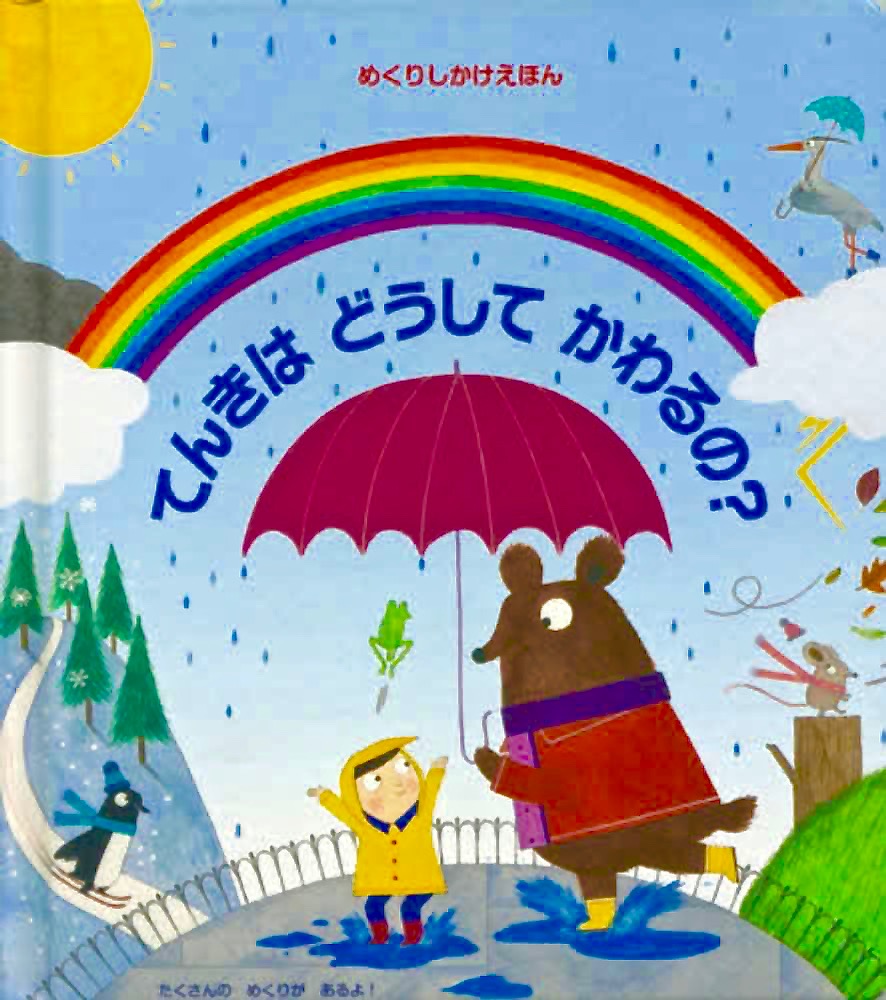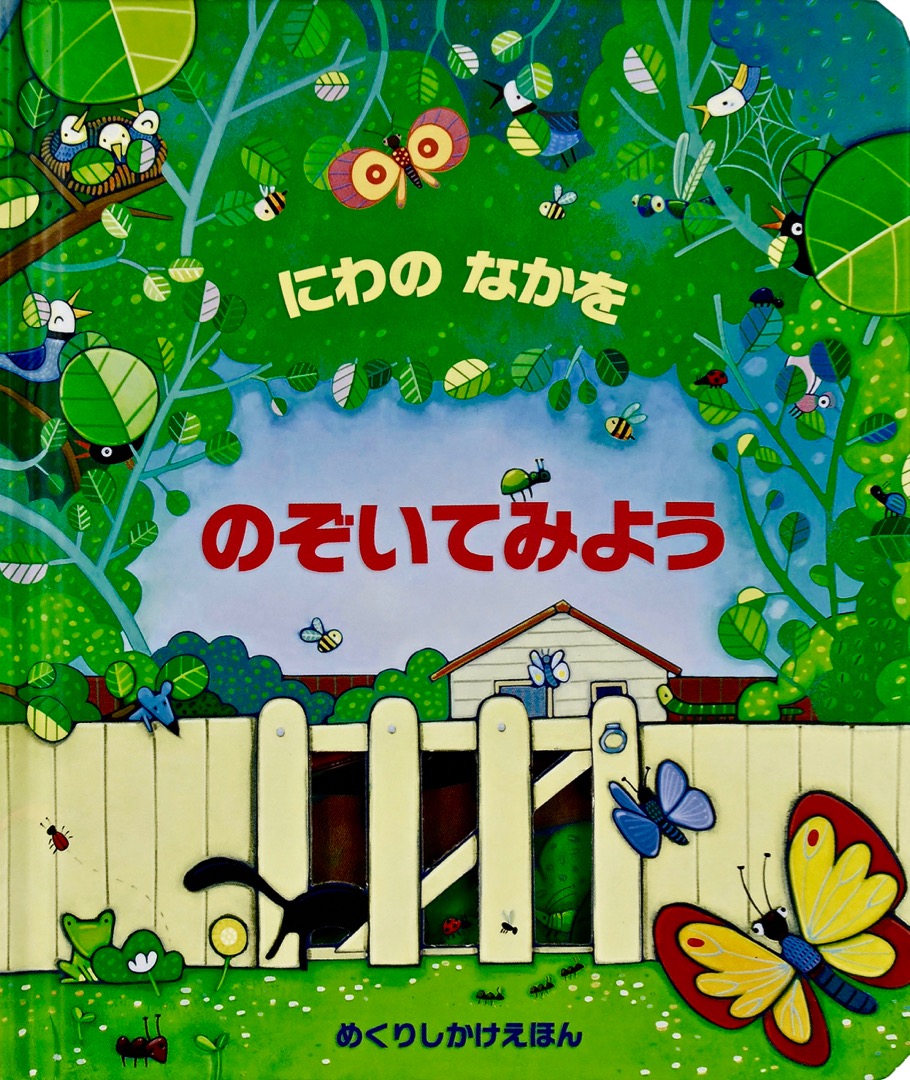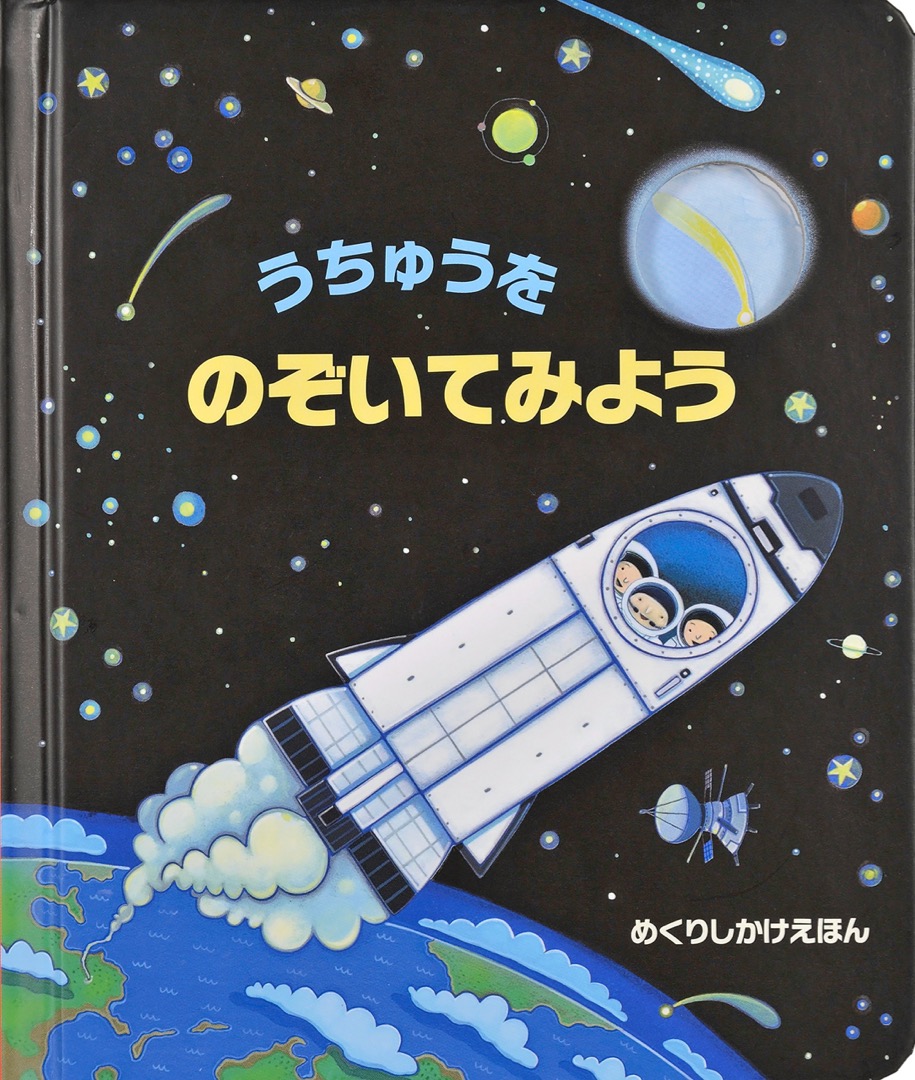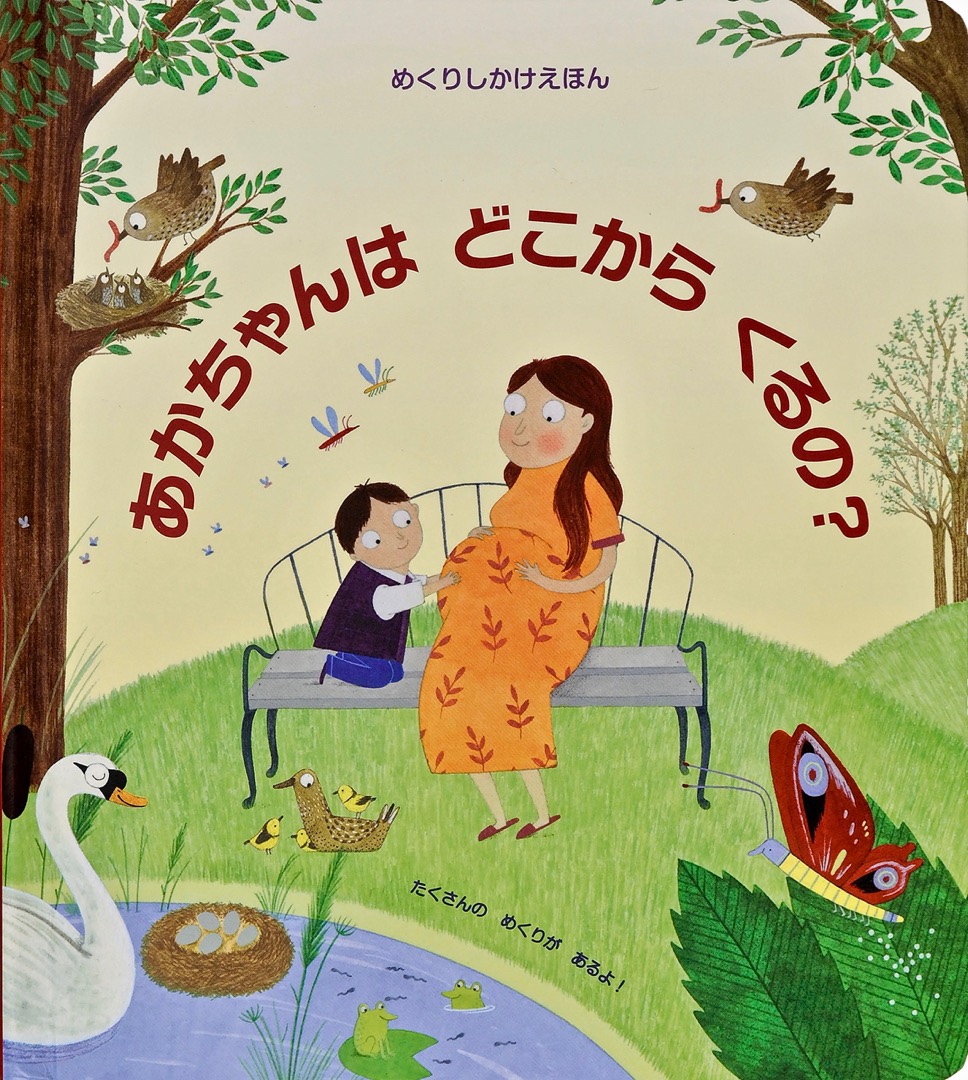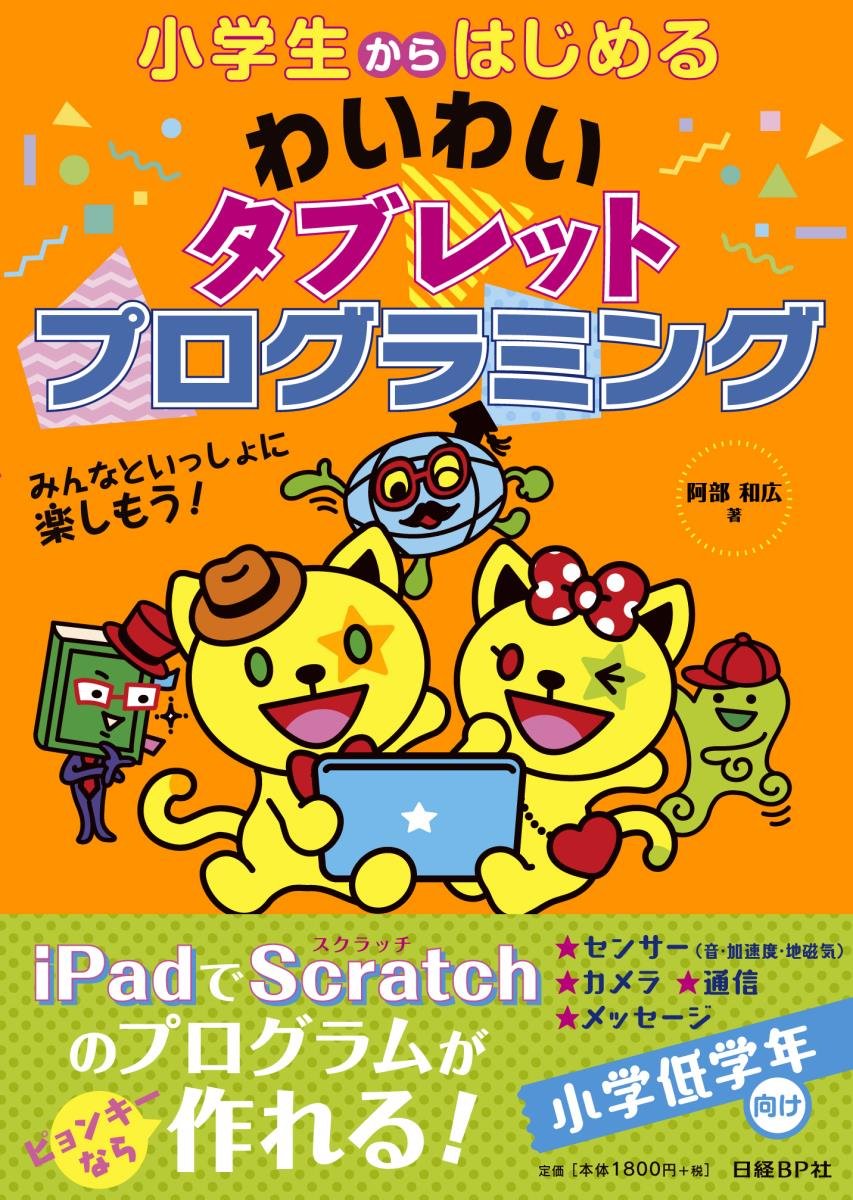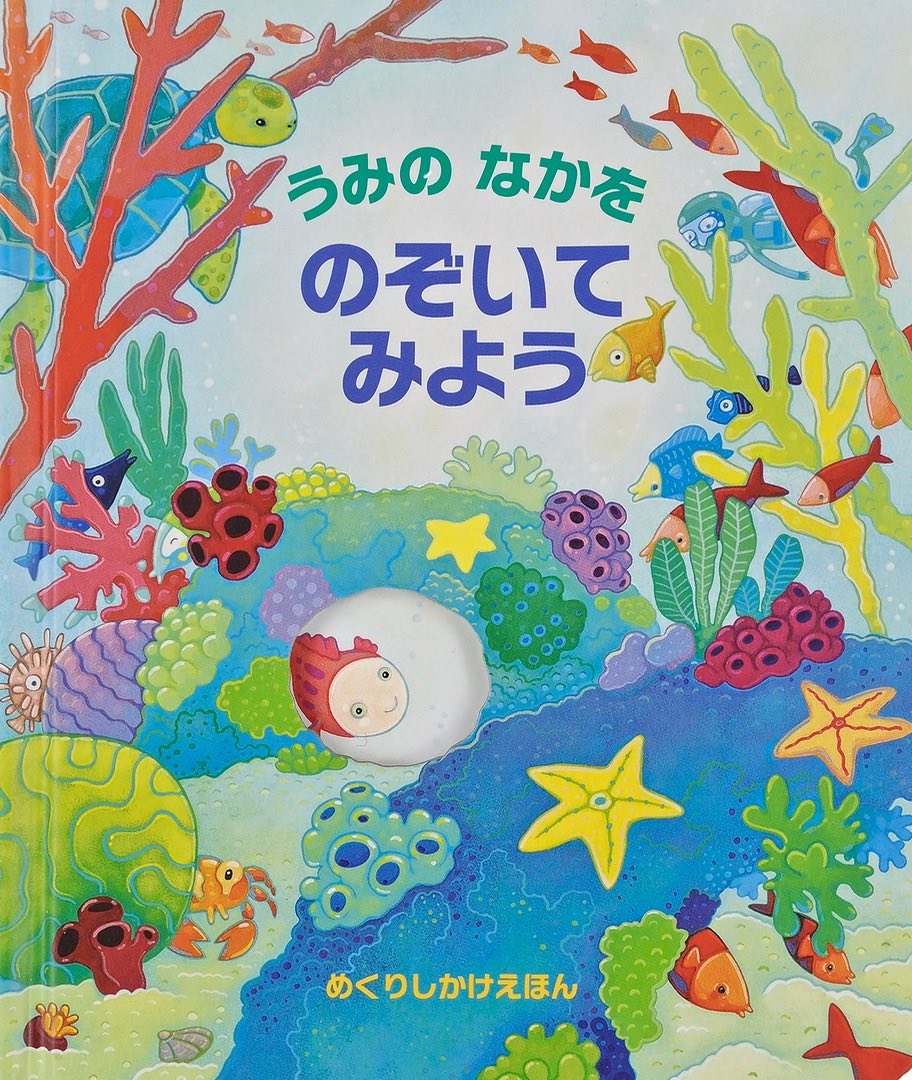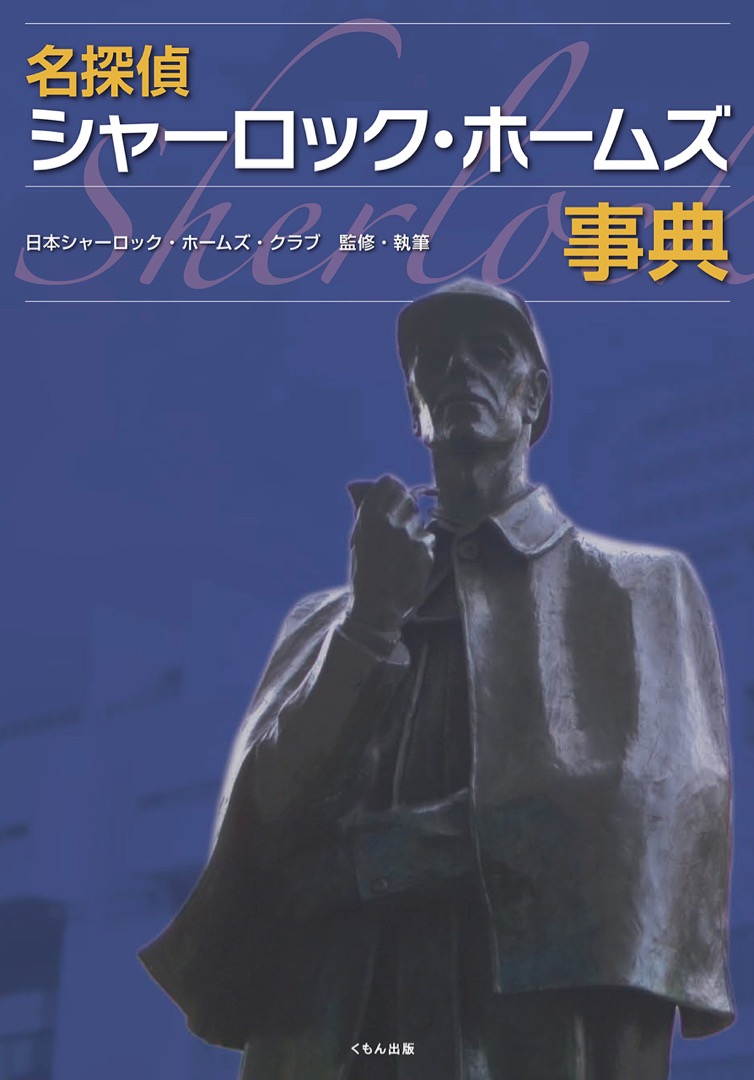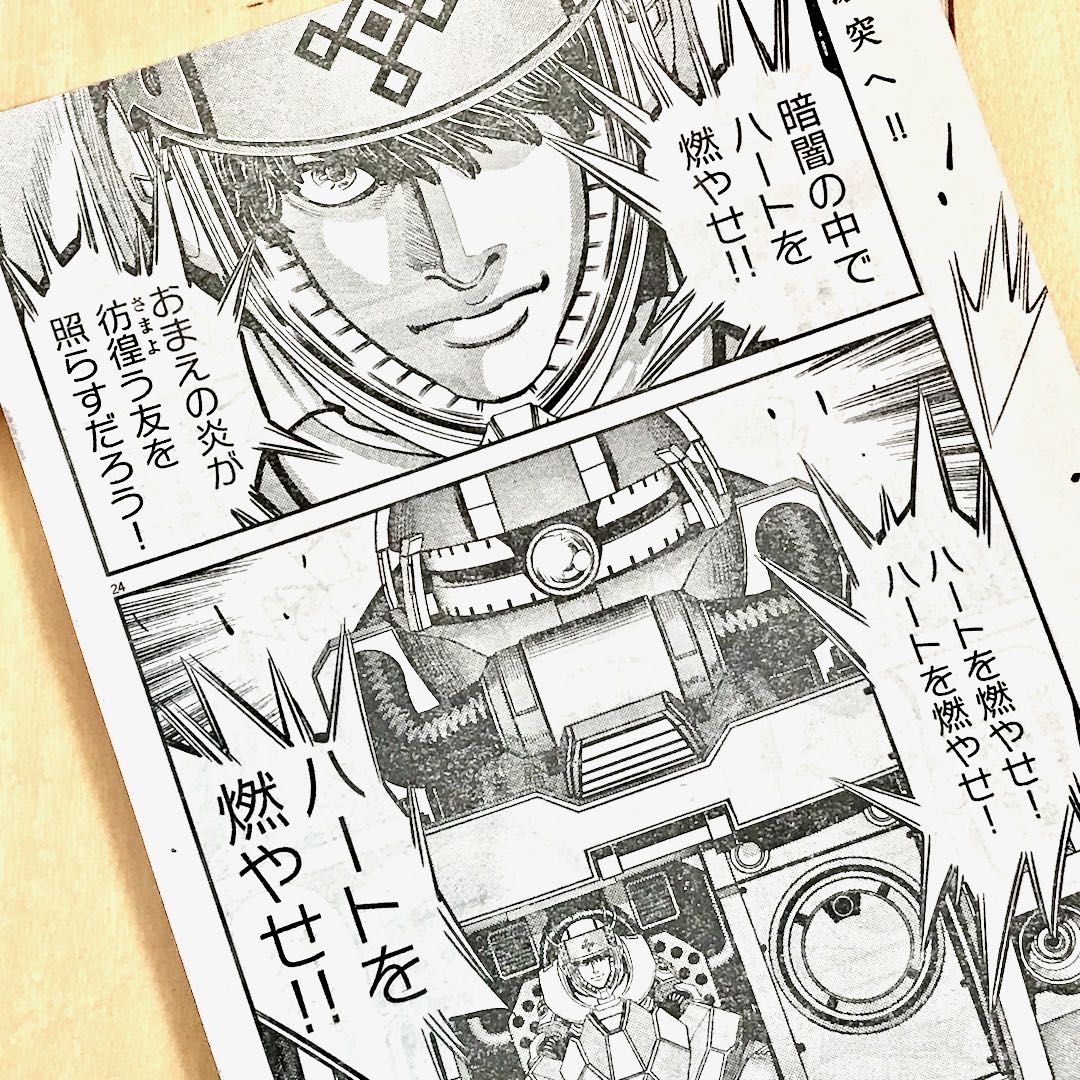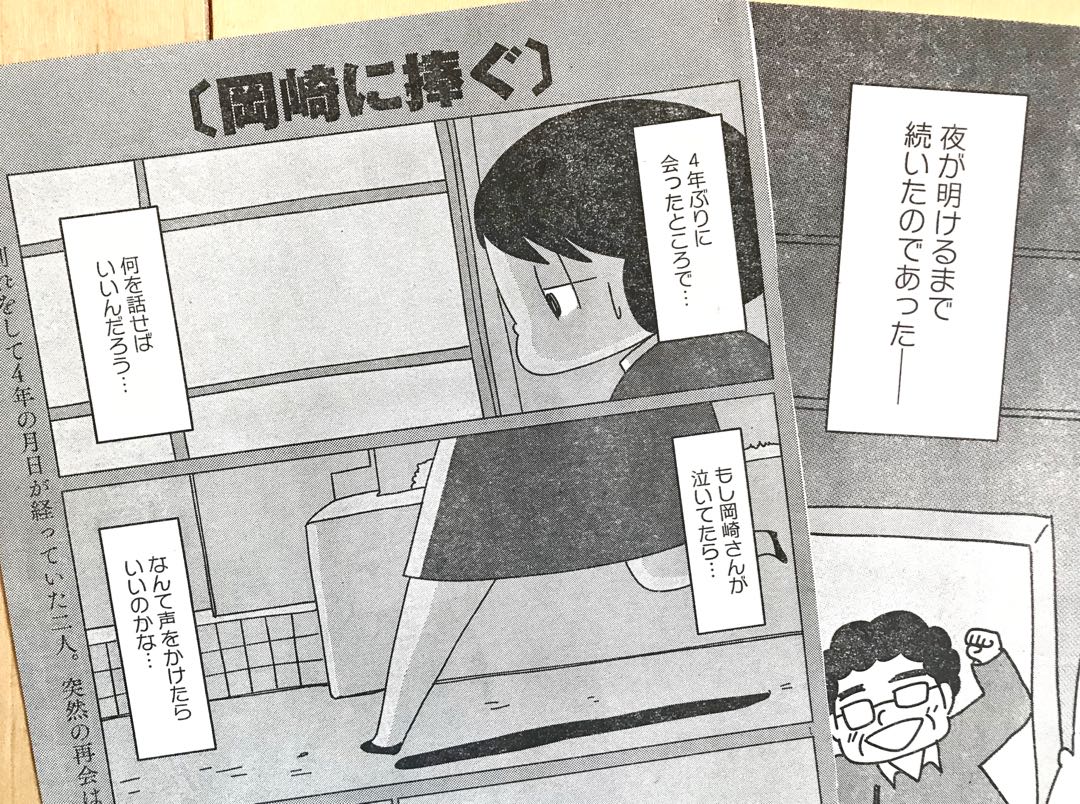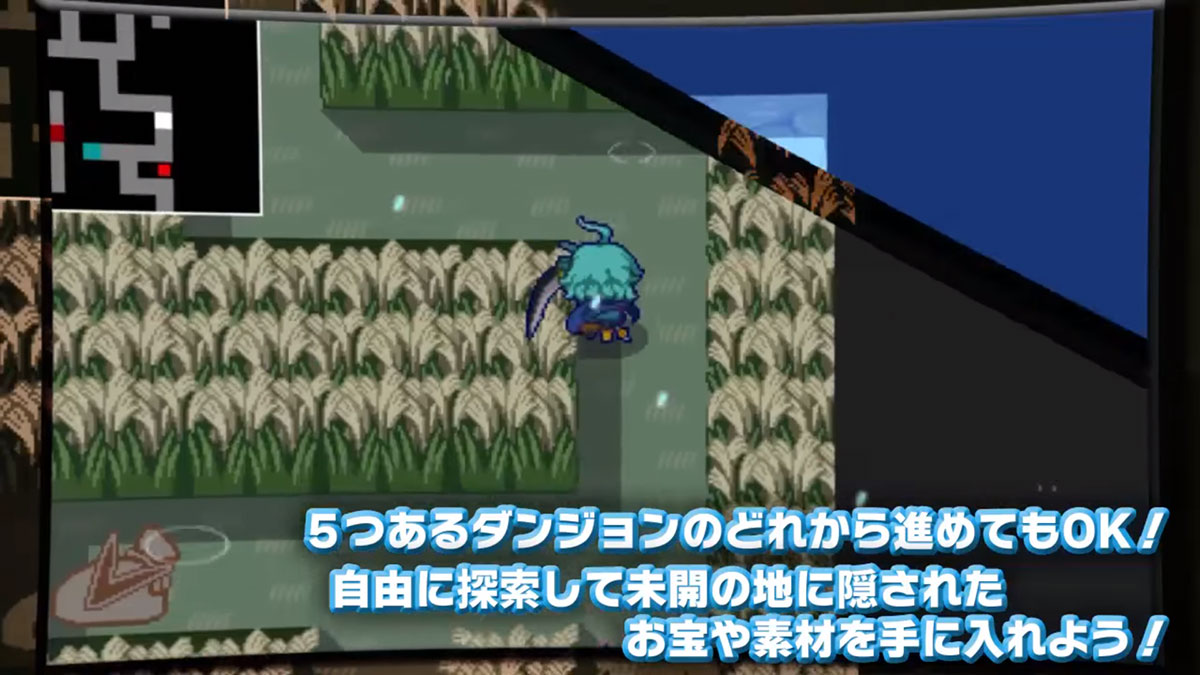
ジョブマッチ交流会 大阪のうめ吉
大阪府堺市、さかいJOBステーションなどが主催の「さかいジョブマッチ交流会」の案内チラシです。A4判の裏面で大量に使用。
右側は部分拡大したものです。
府政だより 大阪のうめ吉
大阪府の「府政だより」です。「もずやんの大阪ひとっとび」のタイトル
です。
TV番組 さとうゆたか
千原せいじのKids's World
同じ番組内…。
これも…。
出前講座 大阪のうめ吉
大阪市立総合生涯学習センターの「出前講座」案内のパンフレット(A4判三つ折)です。
この書体、フォントワークスやモリサワからも販売されてますから、印刷物では、もうスタンダードな書体ですね…。
ボランティア情報誌 大阪のうめ吉
大阪市社会福祉協議会のボランティア情報誌「COMVO」(B5判16ページ)7月号で。
3ページで使用。「大阪のボランティアが被災地・東北で交流活動」。中見出しで4本(次のページ、省略)。「天神祭ごみゼロ大作戦 ボランティア募集」の見出しです。
むずかしそうな本 さとうゆたか
書名:コンテナ・ベース・オーケストレーション
著者:橋本 直哉、須江 信洋
発行:翔泳社
ハルカス情報紙 大阪のうめ吉
大阪市阿倍野区の日本一の超高層ビル、あべのハルカスのA4判4ページ
の情報紙「ハルカスライフ」。
先日のポスターのビアガーデンが1面に。今回は使用フォントが増えてい
ます。
この書体、本当にたくさん使われています…ね。
セルフスタンド 大阪のうめ吉
大阪市平野区喜連(きれ)にあるセルフ式のスタンド。
店舗と、ここの新聞折り込みチラシです。「セルフ喜連」の部分のみの使用です。
この書体は、モリサワやフォントワークスからも販売されているせいで、印刷物では多く使われていますね。
J:COM その2 大阪のうめ吉
同じJ:COM情報誌の別の特集です。
中見出しも含め、見出しで数多く使用。ただしひらかな、カタカナのみ。漢字部分は混植になっています。
この編集をした人も、ニタラゴのかな、カタカナが好きみたいですね。
j:COM情報誌 大阪のうめ吉
J:COM大阪局が加入者向けに発行している情報誌「J:COMマガジン」(120ページ)大阪版7月号の2ページ見開き釣り特集です。
魚の名前に使用しています。